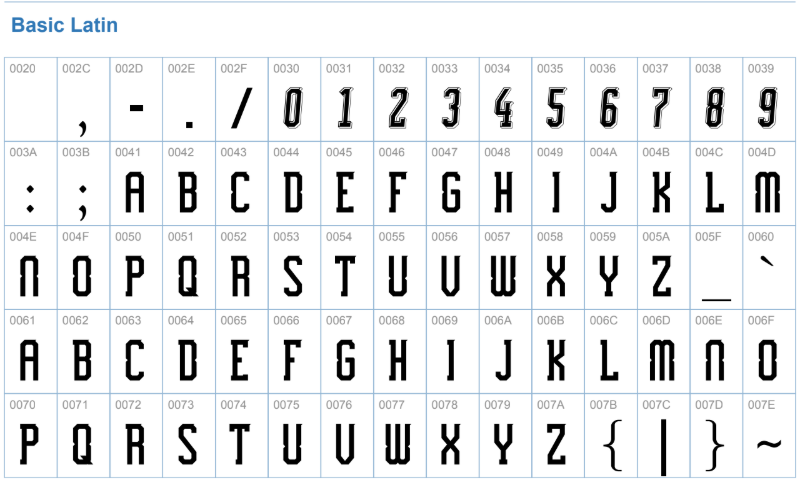
A contagem regressiva para a Copa do Mundo ganhou ainda mais identidade. A nova tipografia da seleção de Marrocos para 2026 foi apresentada oficialmente, mesclando a tradição geométrica da cultura marroquina com a legibilidade extrema que o futebol moderno exige. É o tipo de fonte que nasce para brilhar nos estádios e vestiários.
Mais do que simples letras, a nova identidade visual transforma os nomes nas costas em uma declaração de estilo. O design foi pensado para agradar tanto o torcedor apaixonado quanto o designer gráfico mais exigente. Se você buscava o arquivo para personalizar camisas ou projetos, chegou ao lugar certo.
Estilo visual da tipografia
A fonte foi desenhada com um leve contraste nos traços e prolongamentos elegantes nos numerais, remetendo aos mosaicos históricos do país, sem perder o minimalismo que as transmissões de TV exigem. Os números “7” e “4”, por exemplo, ganharam um corte angular exclusivo. O resultado entrega uma legibilidade absoluta, mesmo em ângulos fechados de câmera.
É moderna sem ser fria, e tradicional sem ser antiquada. O equilíbrio perfeito entre passado e futuro.
Aplicação no uniforme
No manto titular, a fonte aparece em branco com um discreto outline vermelho, gerando um contraste limpo sobre o fundo escuro.
Já no uniforme reserva, a versão chapada em vermelho fechado assume o protagonismo, garantindo uma leitura fácil à distância. A versão third, caso vazada em detalhes, seguirá a mesma lógica monocromática.